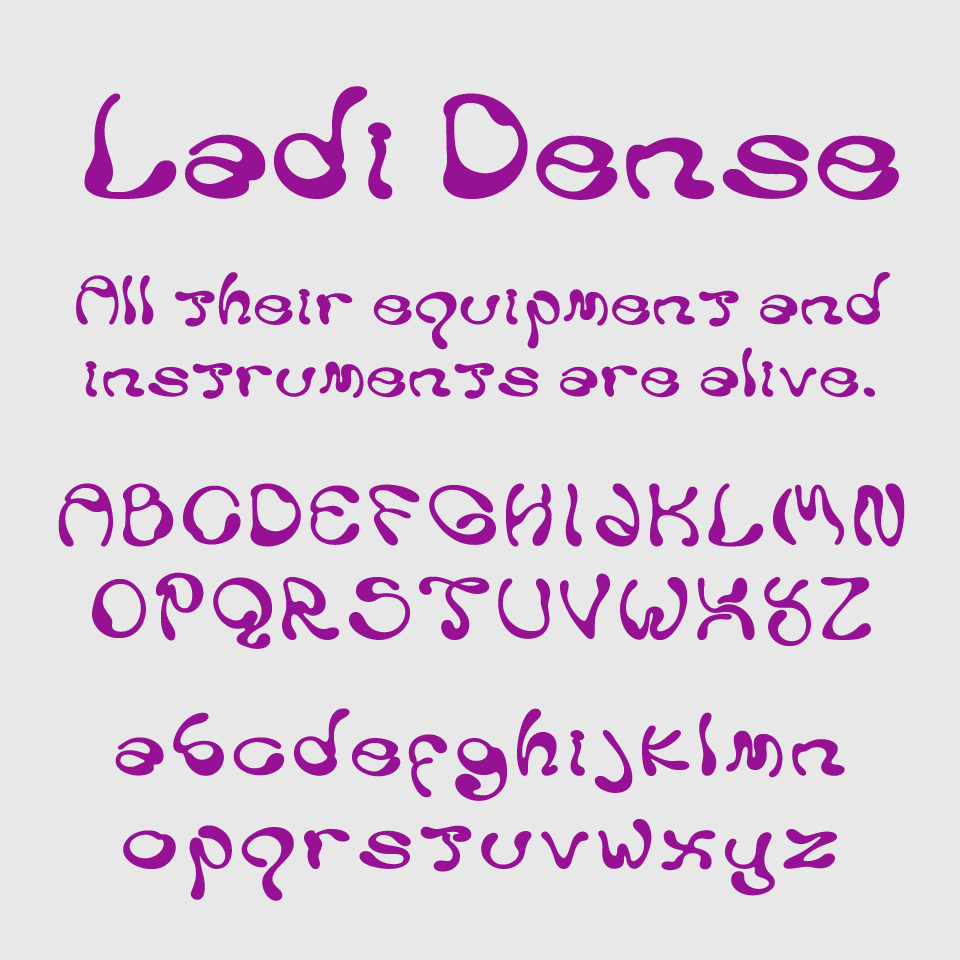
Ladiフォントは、うみょ〜とした水滴のような形状がユニークで、見る人の記憶に残りやすいディスプレイフォントです。
文字の可読性よりもアート性を優先したデザインで、フォルムが不規則に波打つような感触があります。Y2Kやサイケやグルーヴィーな世界観にぴったりなフォントです。
使用する色や背景との組み合わせで、楽しさや奇抜さをさらに引き出せるフォントです。デザインで遊び心を出したいときにおすすめなフォントです。